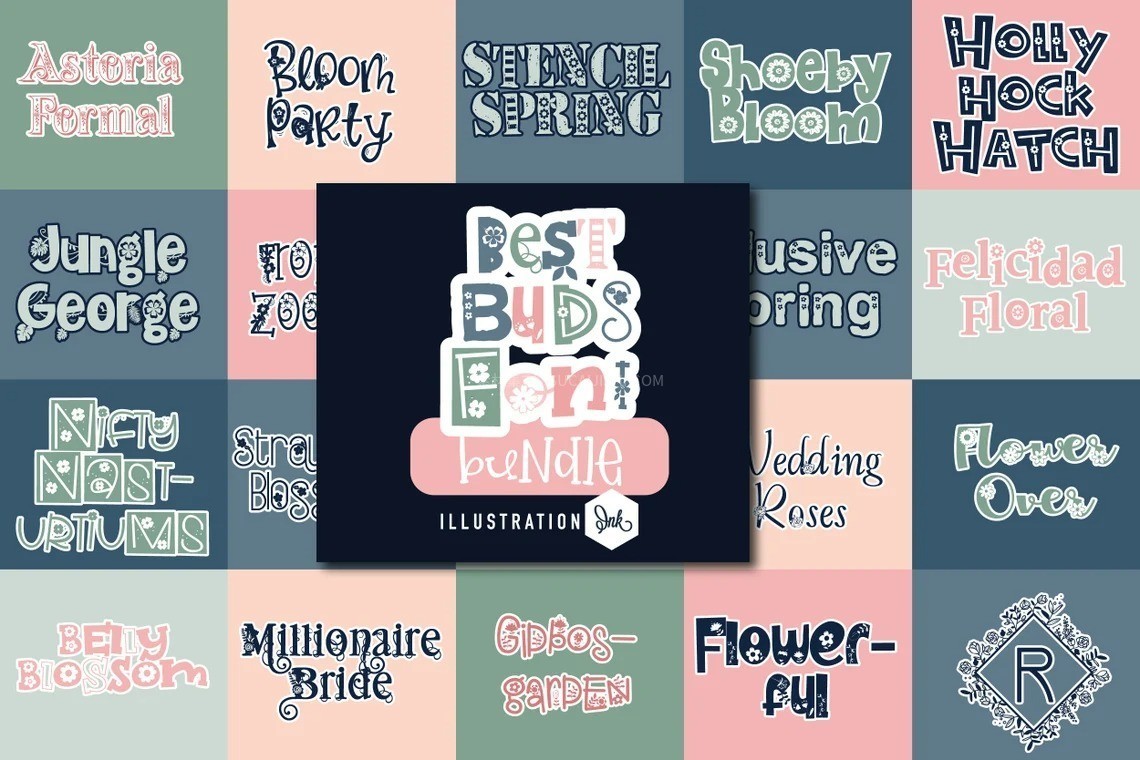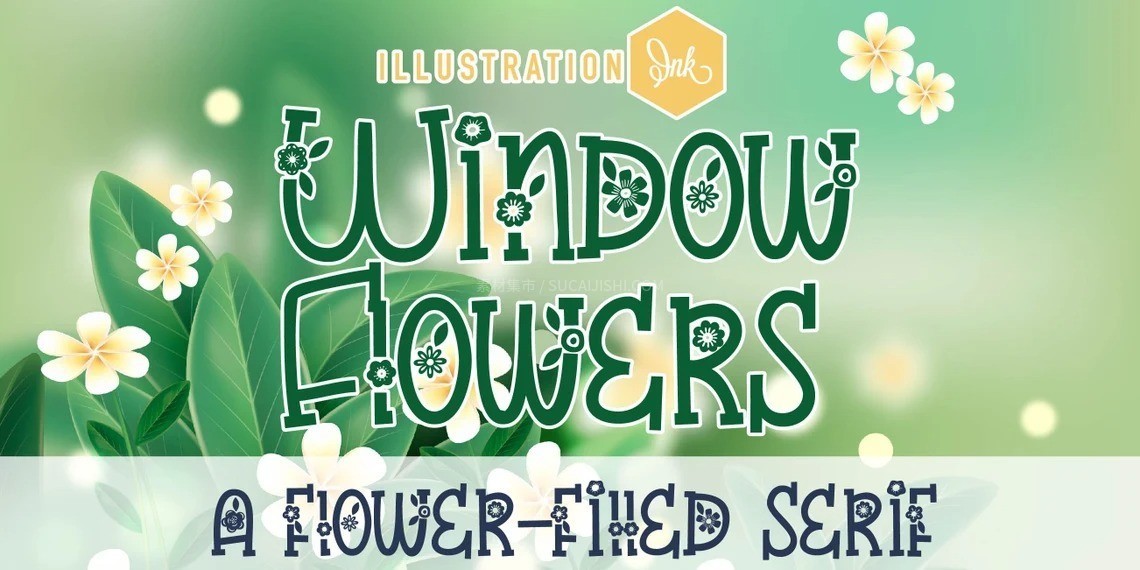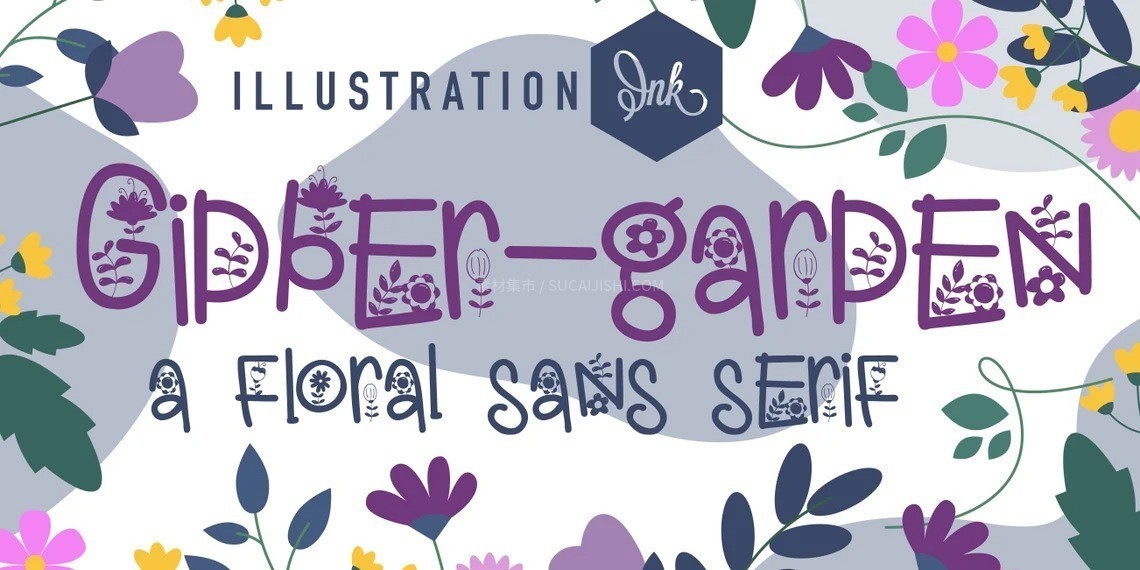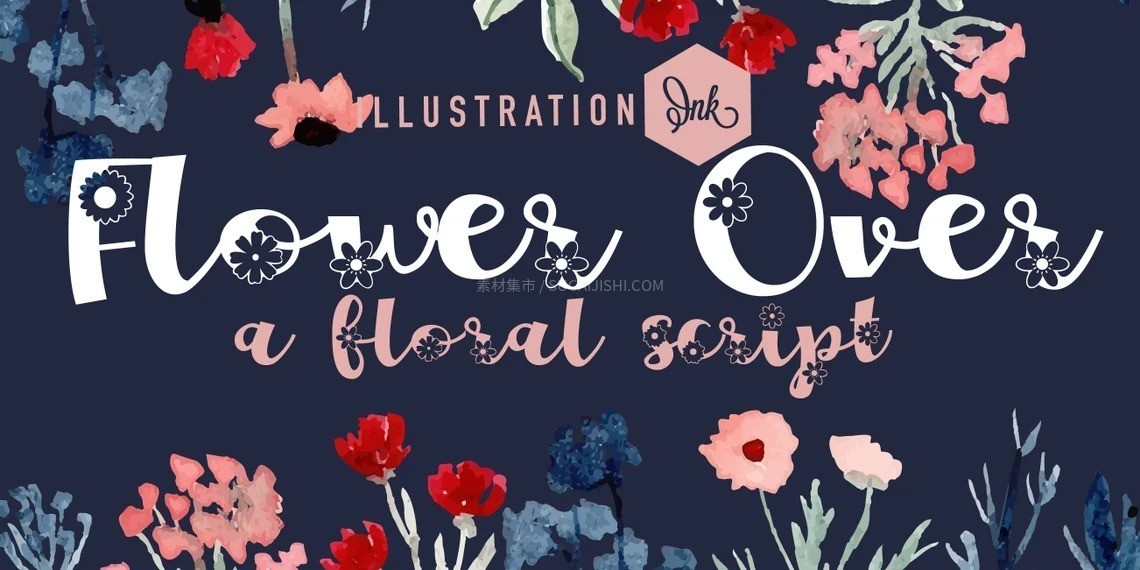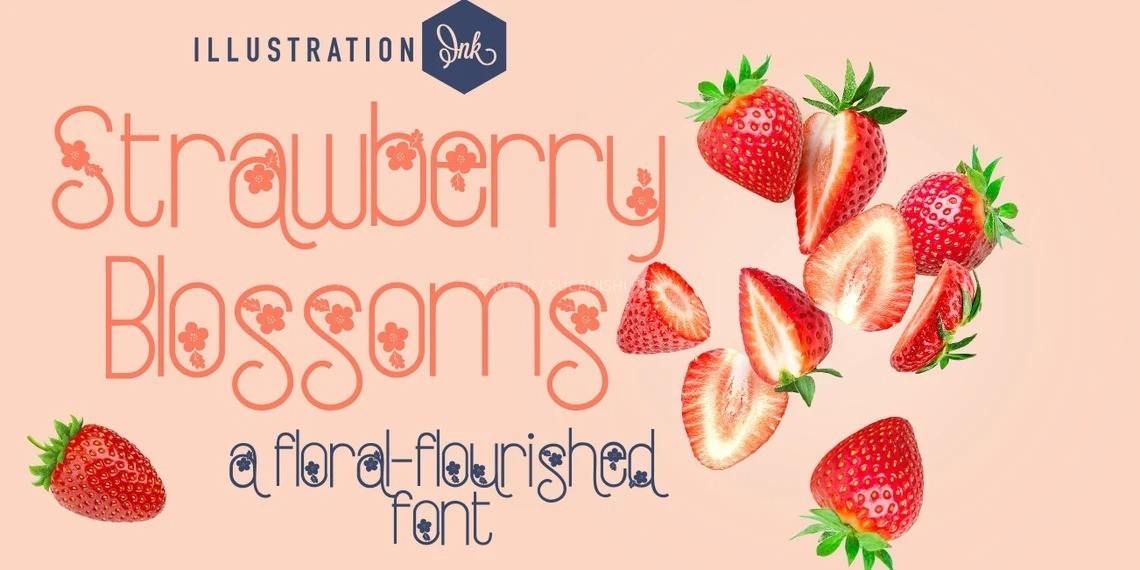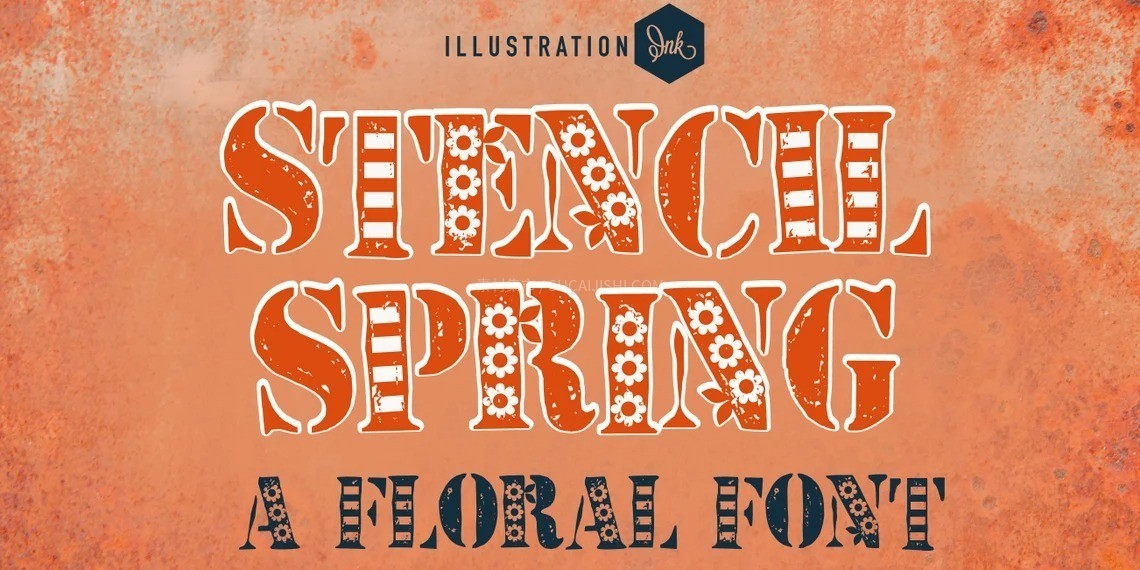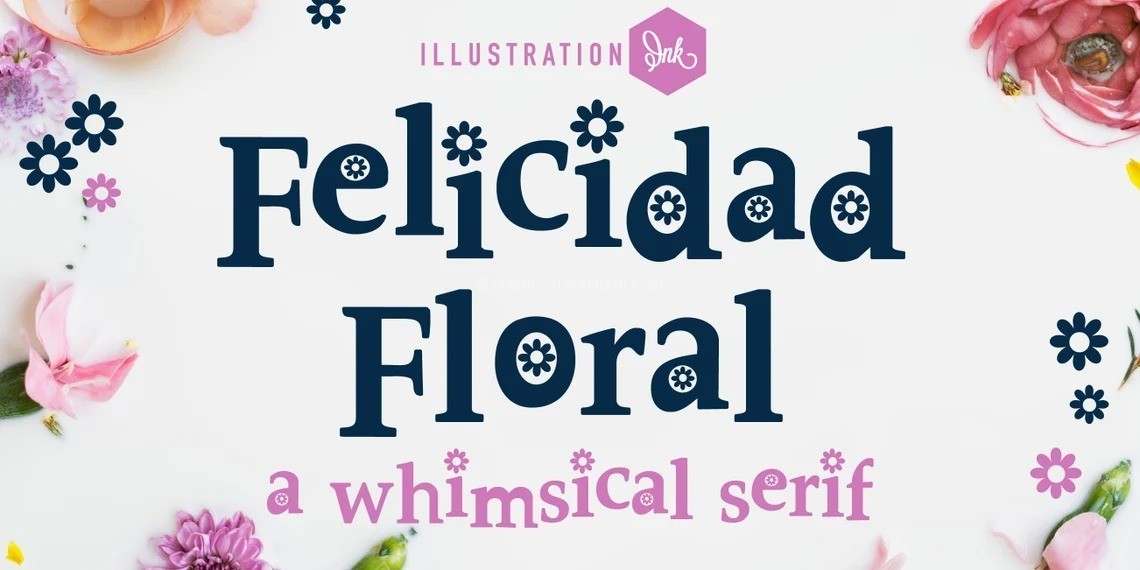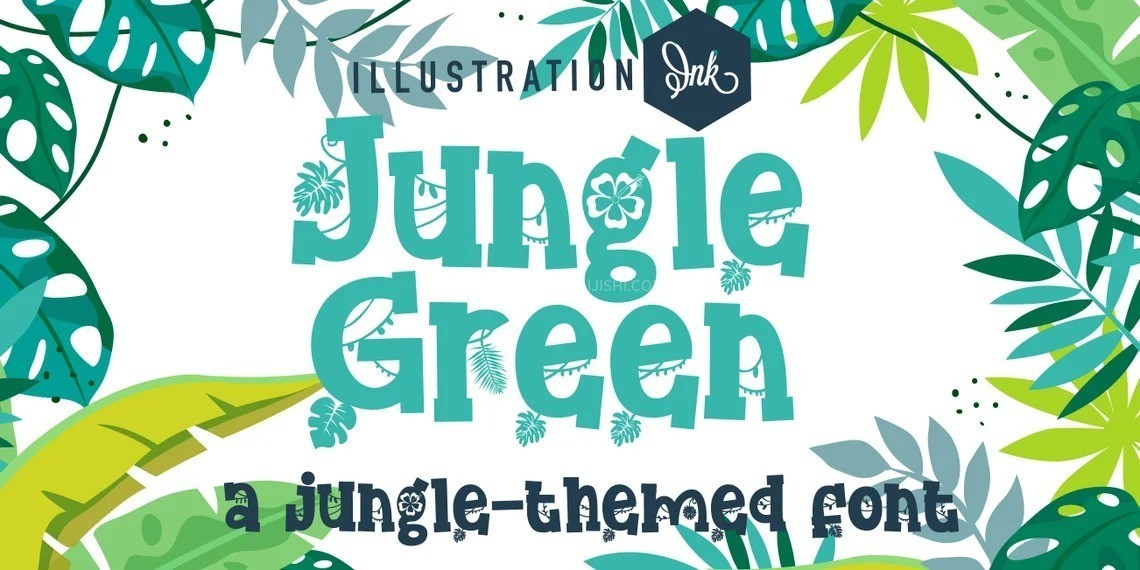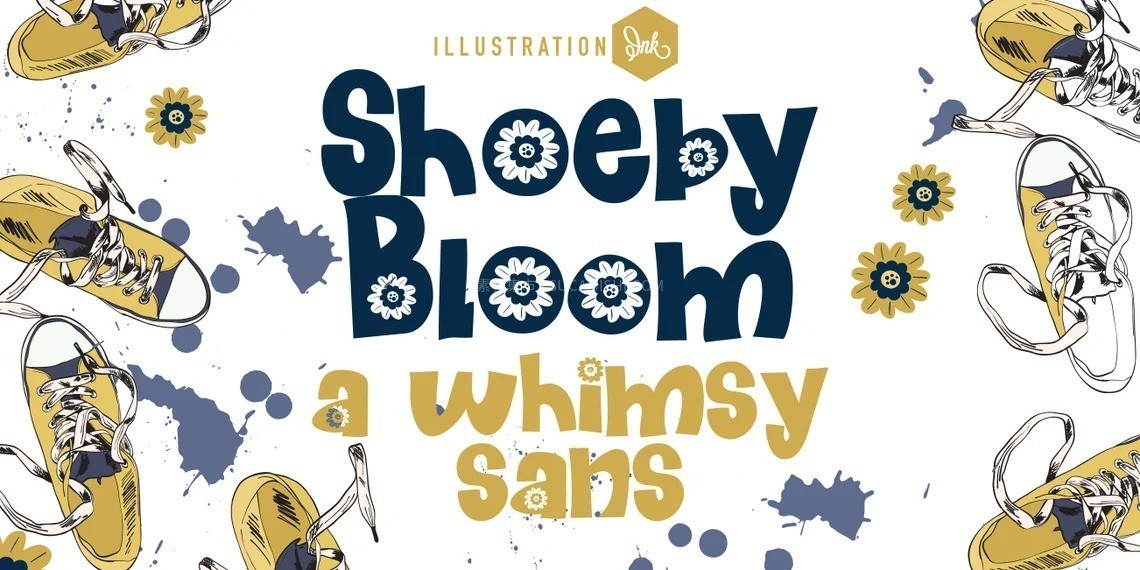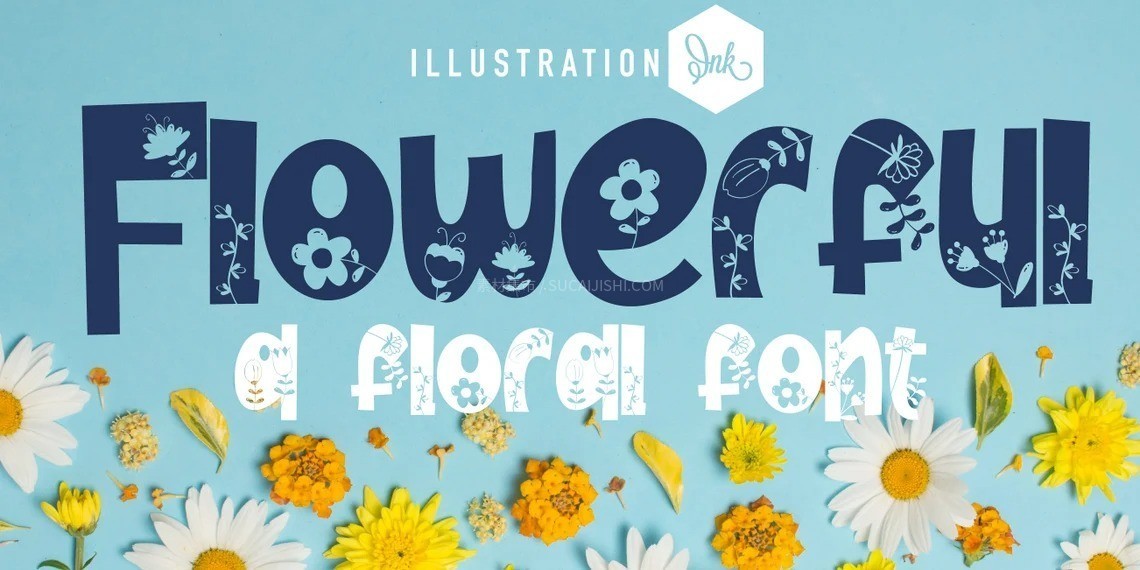
20款创意手绘花纹图案装饰字体包
这款宝藏级字体包精选了 20 款自带手绘花纹的图案装饰字体,每一款均由纯手工绘制,保留了独特且自然的手作质感。无论是用于品牌视觉、营销海报、网页设计还是实体印刷,它都能为你的设计注入充满温度的个性与创意。如果你正在寻找能让作品瞬间脱颖而出的秘诀,这套充满手绘风格的字体包绝对是你的完美之选!